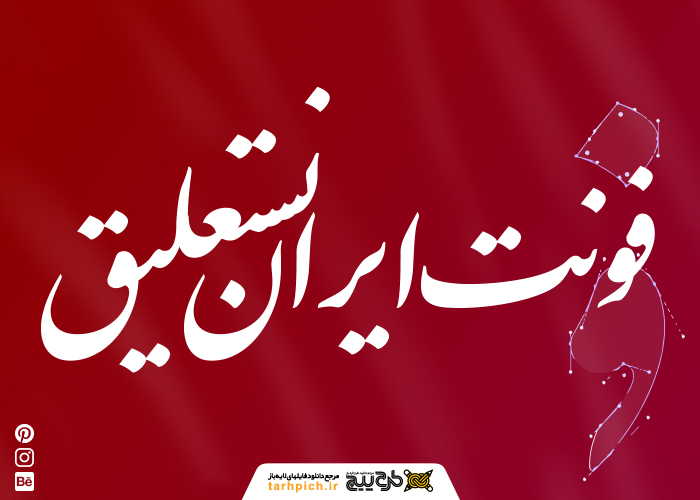
فونت فارسی ایران نستعلیق را میتوان اولین فونت فارسی یونیکد شده استاندارد در نظر گرفت. فونت ایران نستعلیق یکی از فونتهای فارسی شکسته است که طرفداران زیادی نیز دارد.فونت Iran Nastaliq از لحاظ بصری زیبایی فراوانی را به طراحیها میدهد، دلیل این مورد را هم میتوان در شکسته نویسی این فونت پیدا کرد. برای دانلود فونت ایران نستعلیق به صورت رایگان کافی است از طریق لینک سمت راست بالا اقدام کنید. در حال حاضر 3 نسخه از فونت ایران نستعلیق طراحی شده است که ما برای شما در فایل زیپ قرار دادهایم، با دانلود هر 3 نسخه فونت برای شما قابل دسترسی خواهد بود. از فونت ایران نستعلیق بیشتر طراحان گرافیک استفاده میکنند چرا که جنبه زیبایی بصری این فونت در مقابل خوانایی، بیشتر است.اگر به دنبال دانلود فونت هستید طرح پیچ بهترین گزینه است .
فونت ایران نستعلیق را حسین زاهدی برای اولین بار به سفاش شورای عالی اطلاع رسانی طراحی کرده است. این اولین نسخه از یک فونت رایگان ایرانی بود که به صورت استاندارد طراحی شده بود.